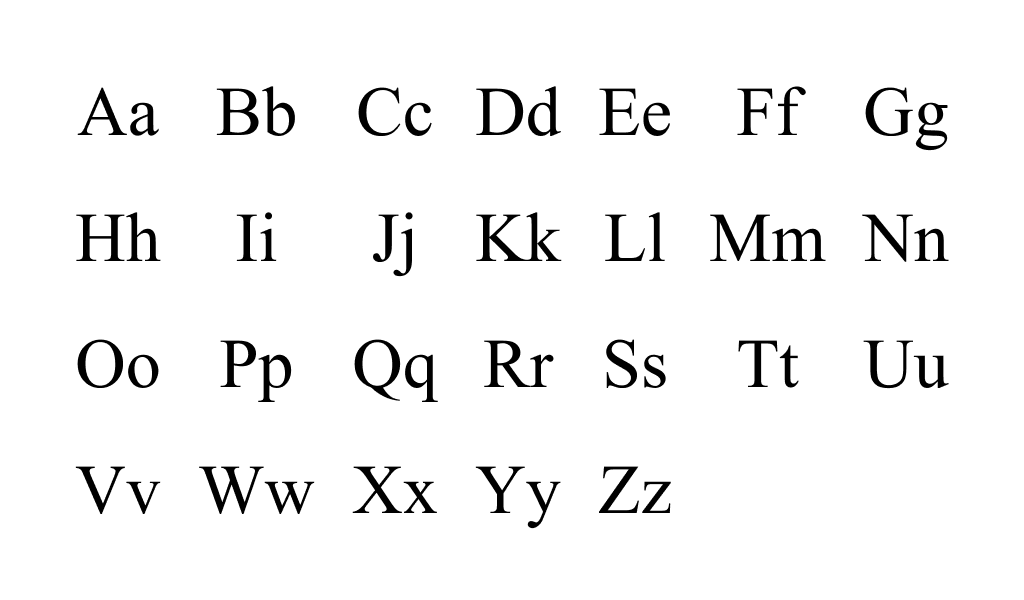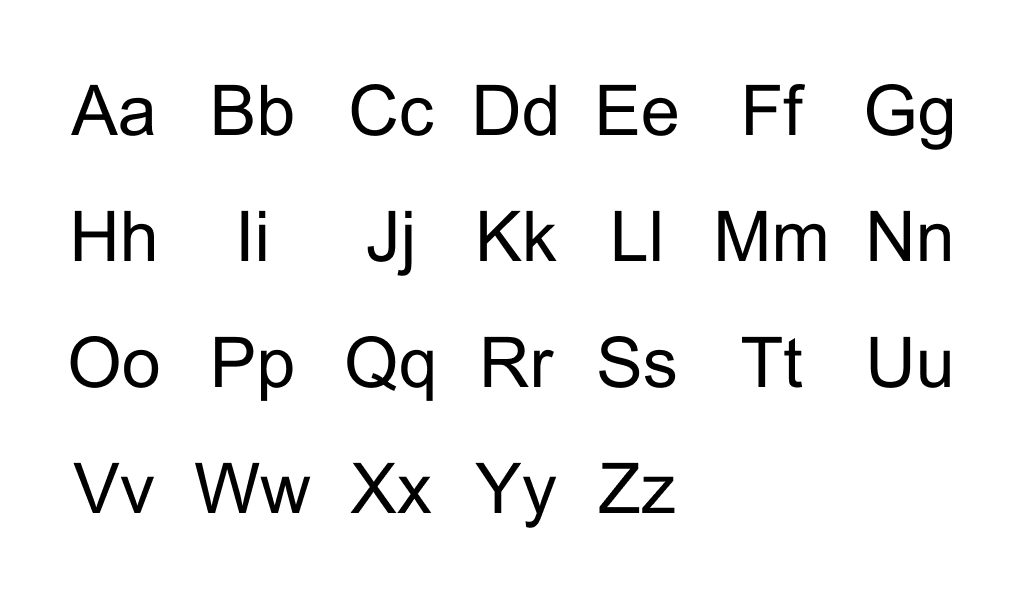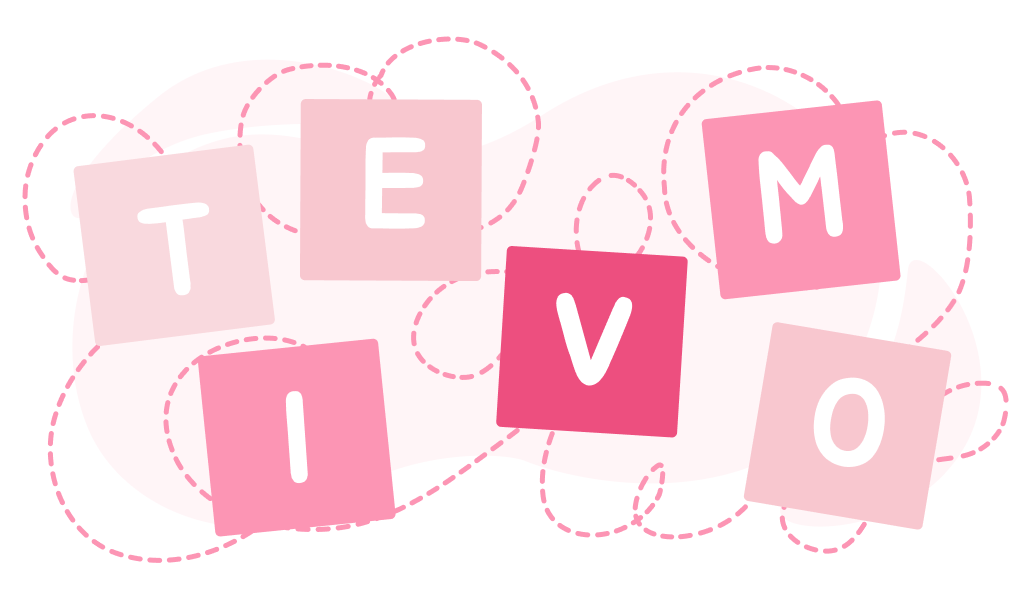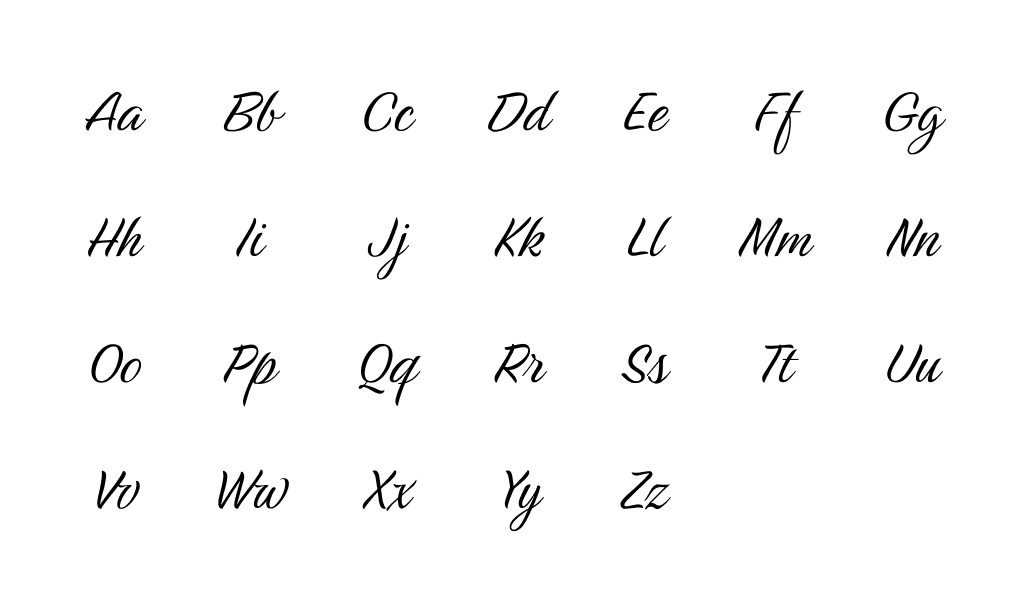
La tipografía ha existido en la humanidad durante cientos de años. Cada uno de nosotros entra en contacto con este fenómeno a diario, hojeando el feed de nuestra red social favorita, leyendo las composiciones de las etiquetas de los productos en la tienda y mirando carteles publicitarios.
La tipografía es el diseño visual del texto, un elemento importante de la marca y un componente clave de la composición.
Crear logoSe sabe que la gente dominó el arte de la inscripción hace más de mil años, mucho antes de la aparición de dispositivos especiales para imprimir. Cada elemento fue cuidadosamente pensado, dibujado en forma de borrador y solo luego transferido al papel en el texto principal.
La tipografía incluye muchos aspectos: desde la maquetación de periódicos y revistas hasta el desarrollo de fuentes para logotipos. Con el desarrollo del progreso tecnológico, comenzó a extenderse por todas partes: ahora sus métodos y técnicas se utilizan no solo en las editoriales.
La tipografía moderna es "responsable" no sólo de la legibilidad del texto, sino también de su diseño gráfico.
La inscripción debe evocar ciertas asociaciones y emociones en el lector, impulsar acciones específicas.
Antes de sumergirnos en el fascinante mundo de la tipografía, acordemos cierta terminología. Los términos «fuente» y «tipo de letra» se utilizan a menudo como sinónimos: esto no es del todo cierto. Un tipo de letra es un conjunto de fuentes, mientras que una fuente es uno de los estilos contenidos en un tipo de letra.
Todos los tipos de letra existentes se dividen en cuatro tipos principales: antiqua, grotesco, escrito a mano y display.
Antiqua (también conocido como «estilo humanista») es un tipo de letra con serifas, pequeños elementos que van más allá de los componentes principales del carácter. Este es uno de los estilos más antiguos y populares y está inspirado en la caligrafía tradicional.
Se cree que la antiqua apareció hace más de 600 años. Los tipos de letra Serif son una opción estricta y “formal” para documentos formales. A menudo se encuentran en publicaciones y documentos impresos. Estas fuentes tienen muchas formas de ejecución, pueden estar en negrita, cursiva, etc. El estilo serif más famoso es Times New Roman.
Lo grotesco ganó popularidad hace relativamente poco tiempo, a mediados del siglo XX. Del estilo humanista mencionado anteriormente, se distingue por un aspecto gótico. El tipo de letra se considera más moderno y claro, muy adecuado para textos electrónicos: es fácil de leer en las pantallas. Este tipo de letra es una excelente opción para los títulos. Su «representante» más famoso es la fuente Arial.
El tipo de letra escrito a mano es único debido a su arte y sus elegantes curvas. Al igual que la grotesca, la tipografía manuscrita apareció a mediados del siglo XX. La ventaja de las fuentes escritas a mano es la elegancia y la belleza, la desventaja es que son difíciles de leer: no todo el mundo puede analizarlas rápida y fácilmente. La elección de tales estilos debe abordarse de la manera más responsable posible: la fuente debe atraer, despertar interés y no repeler su complejidad.
El tipo de letra de visualización es el más inusual e informal de todos. Las fuentes son muy originales, memorables y crean un estilo único. Estas opciones serán una excelente opción para titulares y logotipos.
Las fuentes tipográficas se destacan en un grupo separado: se utilizan en libros y publicaciones en línea. Su principal ventaja es que son comprensibles incluso en tamaños pequeños.
Elementos básicos de la tipografía.
Conocer los componentes básicos le ayudará a navegar mejor por la variedad de estilos y seleccionar rápidamente lo que necesita.
Interlineado, interlineado: todas estas son designaciones del mismo concepto: la distancia entre líneas. Un interlineado correctamente configurado hace que el texto sea más legible. Si el interlineado es mínimo, el texto se vuelve ilegible y extremadamente difícil de leer. Demasiada distancia también complica la percepción: es necesario ceñirse a la «media dorada» y elegir un valor medio (por ejemplo, la opción «predeterminada»).
El espaciado entre letras, o seguimiento, es la distancia entre caracteres adyacentes. Un espaciado muy pequeño entre letras crea un efecto de encogimiento, demasiado hace que sea difícil separar una palabra de otra. Los parámetros se pueden configurar manualmente: los programas modernos brindan esa oportunidad.
El kerning regula el espacio entre letras solo dentro de las palabras: los valores no se aplican a todo el texto. Muy a menudo, esta herramienta se utiliza al dibujar logotipos: le permite implementar ideas estilísticas inusuales.
Un grafema es la unidad más pequeña de texto: un símbolo (letra, número, signo de puntuación).
Un glifo es una representación gráfica de un grafema en un estilo específico.
Tamaño: el tamaño del carácter verticalmente.
Por separado, digamos algunas palabras sobre las letras: inscripciones con estilos únicos similares a los caligráficos. Las letras no son el tipo principal para formar fuentes, pero a menudo se usan para crear hermosas inscripciones en carteles, etc.
La alineación del texto le permite darle a sus elementos la misma distancia, para hacer un tamaño único de todos sus componentes. Hay cuatro opciones de alineación: izquierda, derecha, centro o justificada. Uno de los más populares es la justificación de texto.
Jerarquía: selección de elementos temáticamente significativos del texto: títulos de varios niveles, barras laterales y otros componentes. Se puede hacer escribiendo subtítulos H1-H5, negrita y cursiva, tamaño de fuente, sombras, etc.
La rubricación es la división interna del texto en bloques semánticos: capítulos, partes, secciones. La rubricación le permite simplificar la percepción del material: debe usarse al diseñar textos grandes: lecturas largas, instrucciones, etc.
Raya: todo el espacio ocupado por texto y elementos gráficos.
¿A qué prestar atención al formatear un texto?
Cualquier texto se crea, en primer lugar, para ser leído y, en segundo lugar, para complementar el concepto visual general. Esté atento a la legibilidad: elija un tono que contraste con el fondo, una fuente comprensible, ajuste el espaciado y otros parámetros. Presta atención a cada elemento: un pequeño defecto puede estropear la impresión.
No recomendamos utilizar muchas fuentes dentro de un mismo material: tres o más estilos corren el riesgo de saturar demasiado el texto visualmente y, por tanto, dificultar su lectura.
Una combinación de fuentes seleccionadas armoniosamente (pueden ser elementos de diferentes tipos de letra) se denomina par de fuentes. Un signo que une estilos en un solo concepto puede ser tanto similitud como contraste. Muy a menudo, un par de fuentes se convierte en una variación de la misma fuente: negrita y cursiva. Se debe tener especial cuidado al combinar tipos de letra Antiqua y Grotesque: no deben entrar en “conflicto” y atraer toda la atención exclusivamente hacia ellos mismos.
No amontones todo el espacio vacío con texto, deja aire. Los párrafos grandes ubicados cerca son repulsivos: pocas personas quieren profundizar en la esencia de dicho texto. Intente expresar sus pensamientos de manera concisa y resalte la información que sea realmente significativa para la percepción.
Recuerda el estilo: elige la tipografía más adecuada al rumbo de tu actividad. No experimentes demasiado si necesitas diseñar un concepto visual para una empresa que no se dedica a una actividad creativa. Y viceversa: no debes elegir fuentes clásicas estrictas para diseñar un proyecto creativo. Recuerde que el tipo de letra incorrecto puede arruinar toda la impresión del proyecto, mientras que la fuente correcta puede hacer que el concepto gráfico sea armonioso y crear su estado de ánimo.
¡La tipografía es increíblemente extensa y emocionante! Sumérgete en el mundo de las tipografías y las fuentes: aprende nuevos estilos y no olvides experimentar con combinaciones, ¡porque es la única manera de encontrar una identidad corporativa!